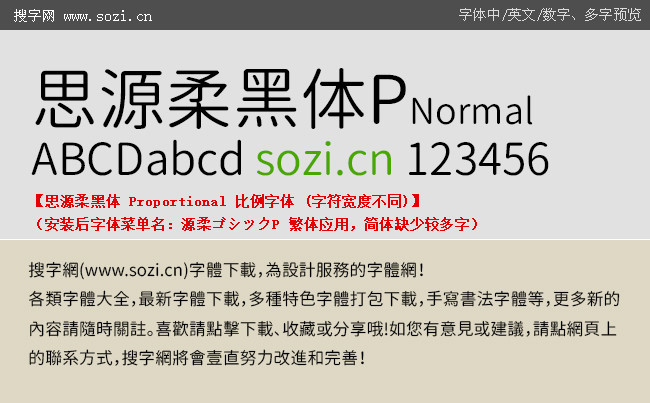
思源柔黑體P-Normal
搜字網(wǎng)給大家提供一款思源柔黑體P-Normal中文字體下載,思源柔黑體由思源黑體改造而來,由日本作者自家製フォント工房制作,所以部分簡(jiǎn)體中文可能會(huì)不顯示,柔黑承襲了「思源黑體」原有的優(yōu)雅,在文字邊角以圓邊進(jìn)行處理,相比原來思源黑體更加柔和,似黑似圓,介于二者之間,而P系列為字符寬度不同的柔黑體系列。適用于排版設(shè)計(jì)、包裝設(shè)計(jì)、海報(bào)設(shè)計(jì)等應(yīng)用。